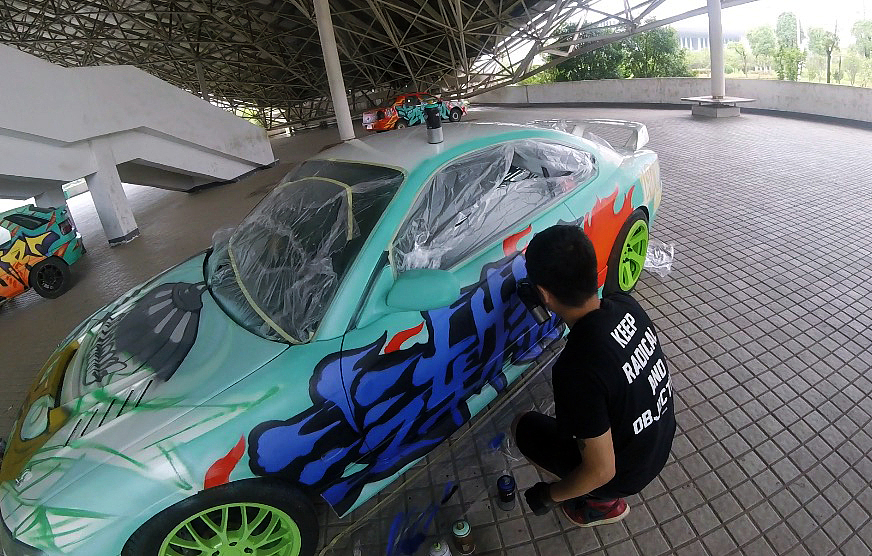
为飘移而生|Silvia·S15 车体涂鸦
给汽车特技人团队的飘移战车s15涂鸦
S15是Silvia车系中的第七代,也是车型发展史上最低谷的一代,不是说其性能不佳,相反,250匹马力输出,加上优秀的FR布局和已经发展到炉火纯青的前麦弗逊后多连杆悬挂布局。港澳地区习惯性将Silvia系列称之为“飞鸡”。
再次增大了车身的尺寸<br>底盘进化的更完美更加适合飘移<br>S15的车身尺寸几乎接近于中级车的尺寸
S15是Silvia车系中的第七代,也是车型发展史上最低谷的一代,不是说其性能不佳,相反,250匹马力输出,加上优秀的FR布局和已经发展到炉火纯青的前麦弗逊后多连杆悬挂布局。港澳地区习惯性将Silvia系列称之为“飞鸡”。
再次增大了车身的尺寸
底盘进化的更完美更加适合飘移
S15的车身尺寸几乎接近于中级车的尺寸
这辆就是我们即将喷的s15
贴上遮蔽膜之后开始准备
在此之前我们还喷过船体和货车<br>场地车的可喷面积相对会少很多<br>而且位置都会比较零散<br>不过相信完成后效果也会比较出众<br>
贴上遮蔽膜之后开始准备
在此之前我们还喷过船体和货车
场地车的可喷面积相对会少很多
而且位置都会比较零散
不过相信完成后效果也会比较出众
前期已经准备好了稿子
S15来自日本的飘移战神<br>我们设计上也融合了日式风格<br>一只穿着日式盔甲的猫<br>战斗感十足的盔甲<br>这个图将喷在引擎盖上<br>用猫作为主公仔形象也是<br>寓意着灵活与速度<br>
前期已经准备好了稿子
S15来自日本的飘移战神
我们设计上也融合了日式风格
一只穿着日式盔甲的猫
战斗感十足的盔甲
这个图将喷在引擎盖上
用猫作为主公仔形象也是
寓意着灵活与速度
创作中。。
侧面以汽车特技人涂鸦字体和LDU
&quot;岔飘联盟&quot;Liberty drifting union LDU
侧面以汽车特技人涂鸦字体和LDU
"岔飘联盟"Liberty drifting union LDU
创作中。。
主体部分很快就完成了
完成后即将参加国际改装车展的开场秀<br>
主体部分很快就完成了
完成后即将参加国际改装车展的开场秀
涂鸦后的战车和其它几辆表演车相比
是全场最拉风飘移车没有之一<br>
涂鸦后的战车和其它几辆表演车相比
是全场最拉风飘移车没有之一
为飘移而生|Silvia·S15 车体涂鸦
二轮行驶特技车&飘移表演
自然嗨爆全场
二轮行驶特技车&飘移表演
自然嗨爆全场
正面完成图
为飘移而生|Silvia·S15 车体涂鸦
右侧图
左侧图